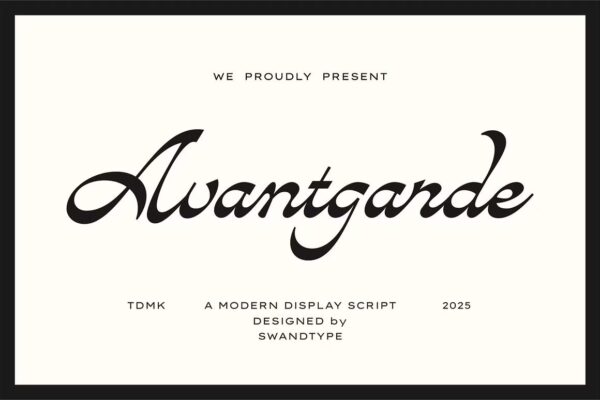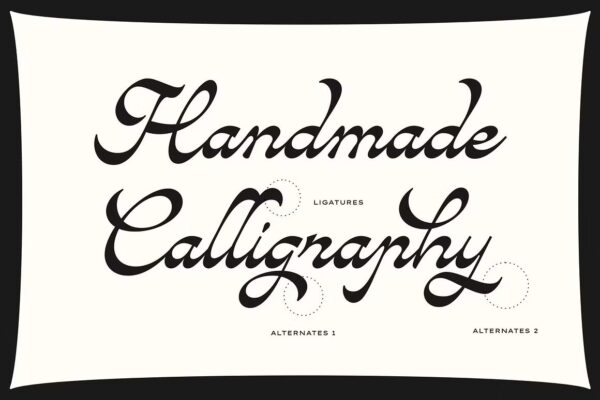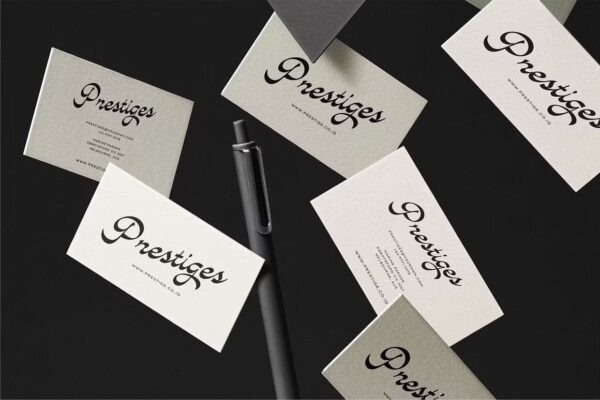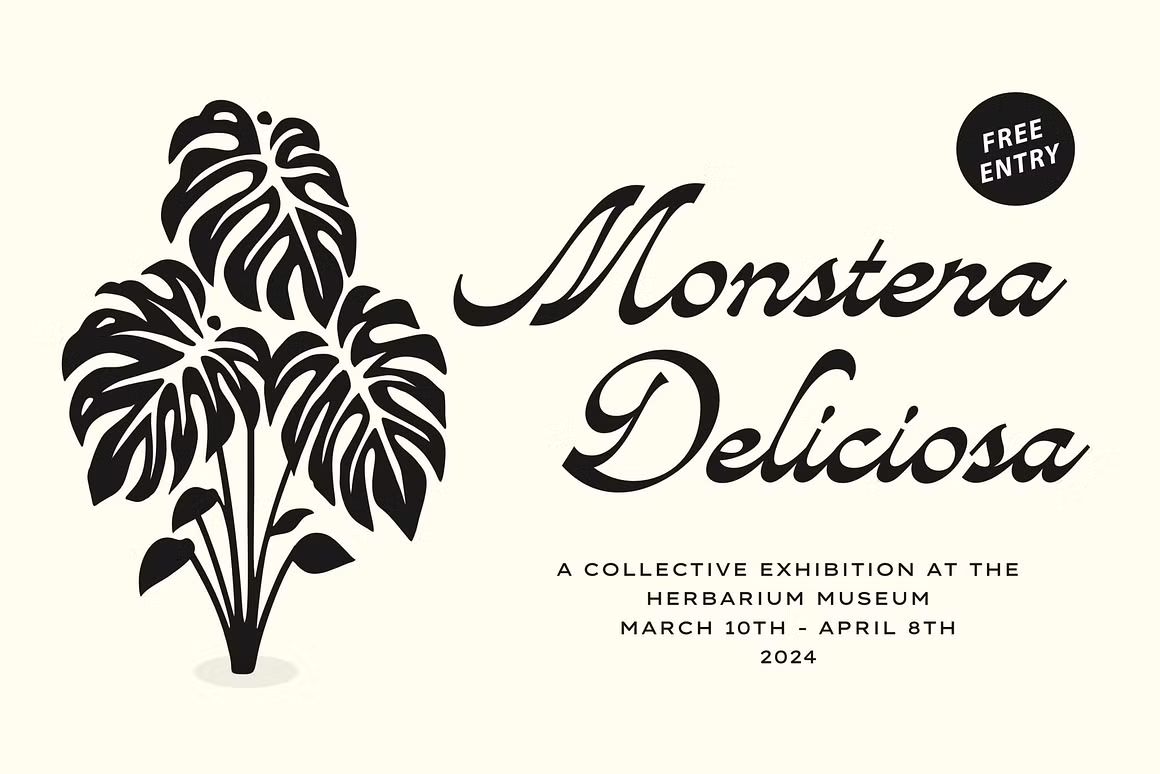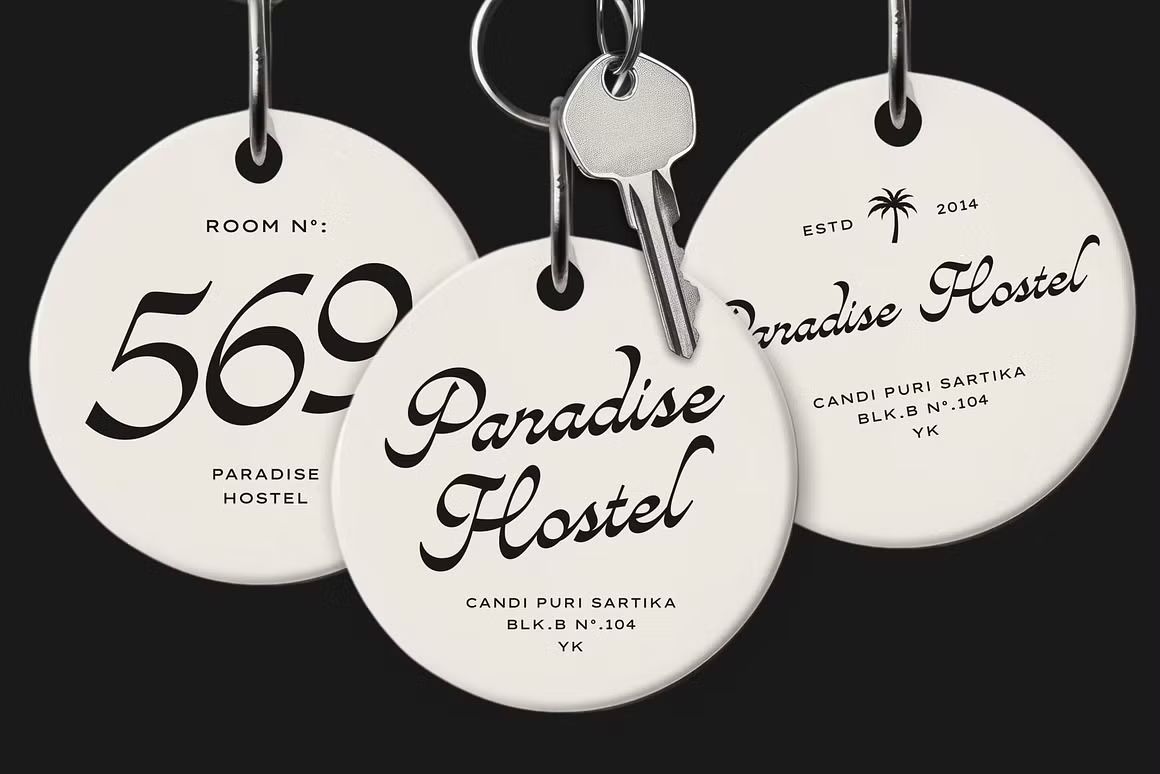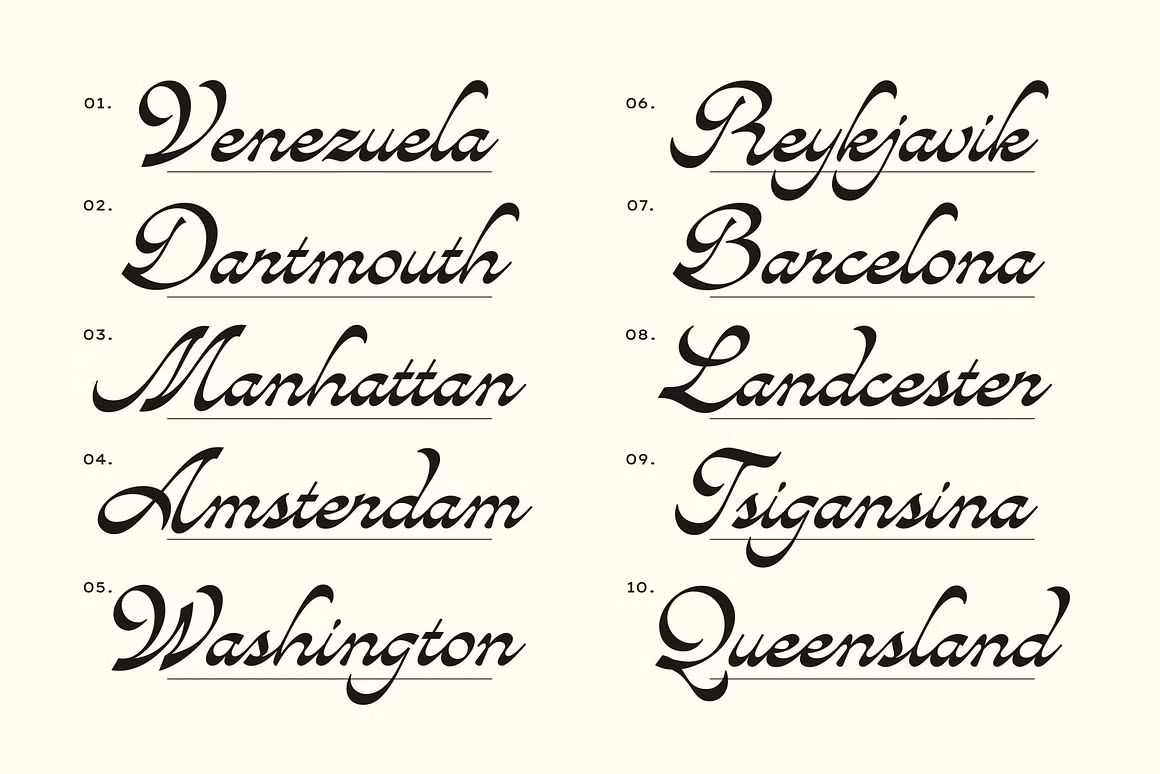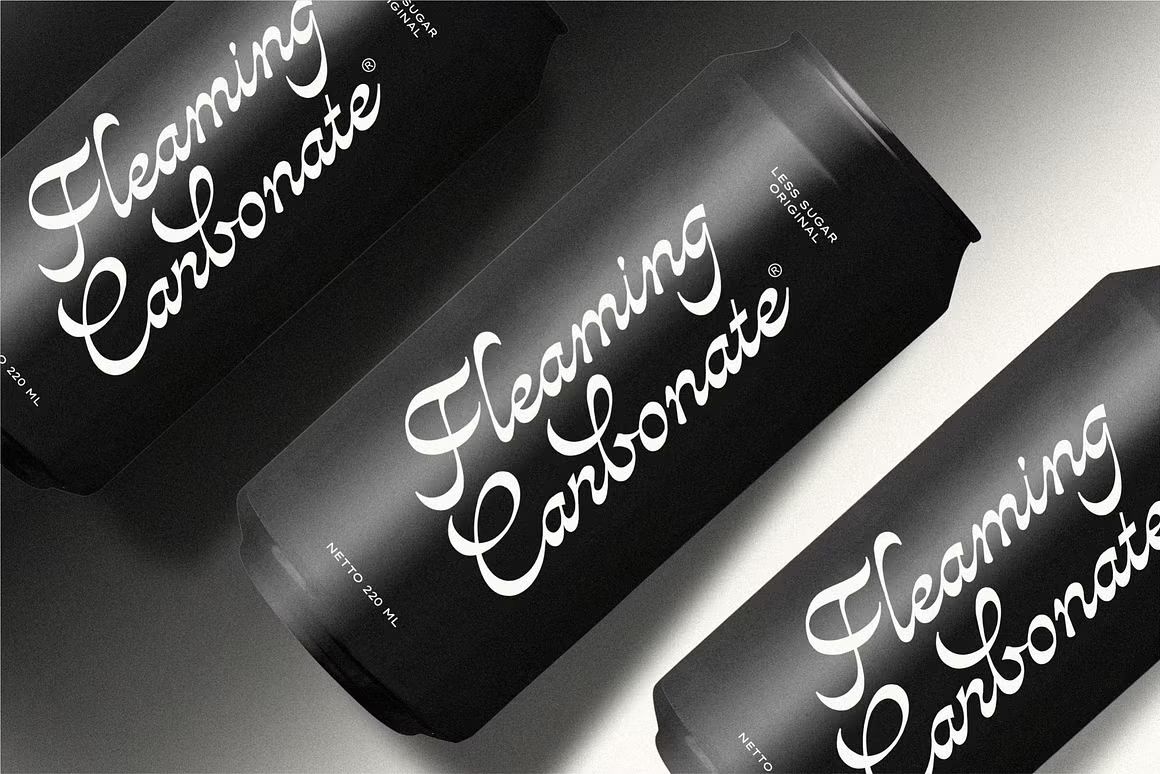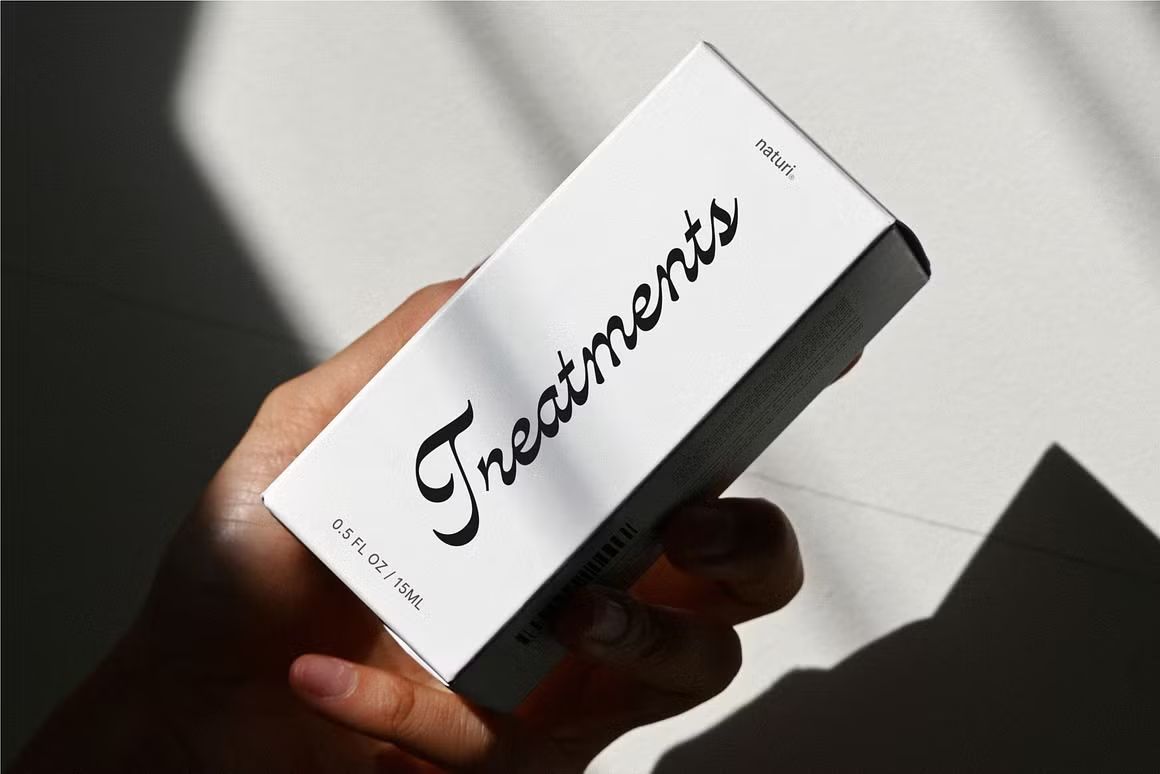
Avandgarde – Script Font
Avandgarde adalah font script modern dan berkelas, cocok untuk branding kreatif, undangan, dan desain fashion. Format OTF/TTF/WOFF, siap digunakan.
Avandgarde adalah font script modern dengan gaya artistik dan berkelas. Menampilkan alur tulisan tangan yang tegas namun elegan, font ini cocok untuk branding kreatif, undangan mewah, logo fashion, kutipan estetik, dan desain editorial. Avandgarde memadukan kesan ekspresif dengan sentuhan profesional, menjadikannya ideal untuk proyek visual yang ingin tampil unik dan sophisticated.
• Script font dengan gaya artistik dan elegan
• Ideal untuk branding, wedding, fashion, dan editorial
• Termasuk huruf besar, kecil, angka, simbol, dan ligatur